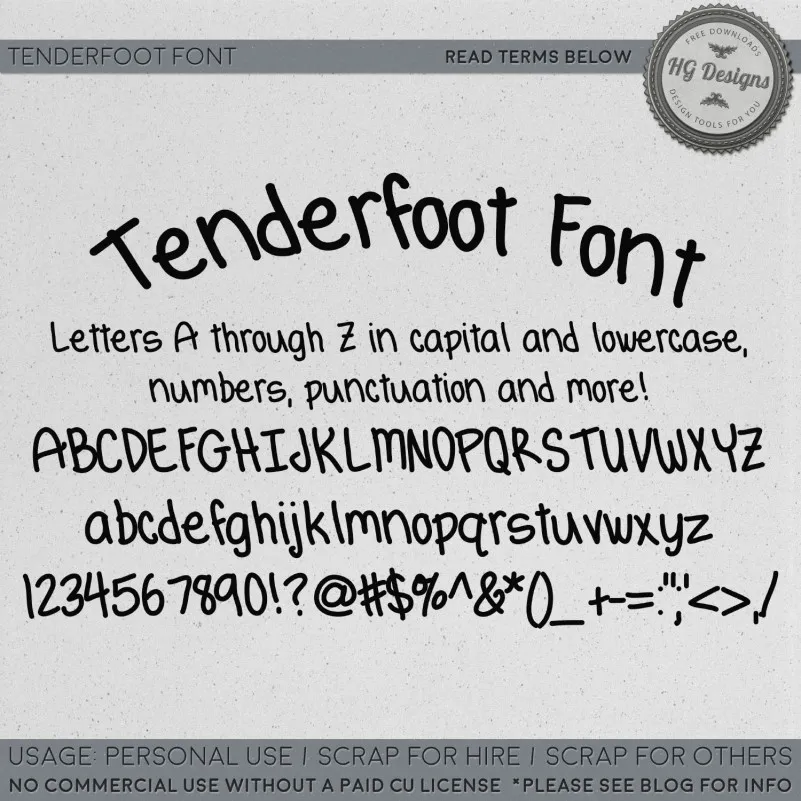
HGTenderfoot Font – Download Grátis
A HGTenderfoot é uma elegante fónt que remete a escrita de uma criança, característica essa que muitos profissionais do design apreciam na sua sutileza e personalidade única. Inspirada nos traços naturais da escrita infantil, ela oferece um toque natural e suave nas suas formas curvas e arredondadas. Essa fonte é perfeita para adicionar um toque de autenticidade em projetos pessoais, desde cartões de convite até mensagens do Instagram. Se você é um designer que valoriza o estilo antigo ou até mesmo um criador digital buscando personalizar seus conteúdos de maneira única e nostálgica, a HGTenderfoot pode ser uma escolha perfeita. A fonte está disponível gratuitamente para uso pessoal, enquanto os licenciamentos comerciais podem ser obtidos através do blog da autora, onde você encontrará todas as informações necessárias no topo da página.